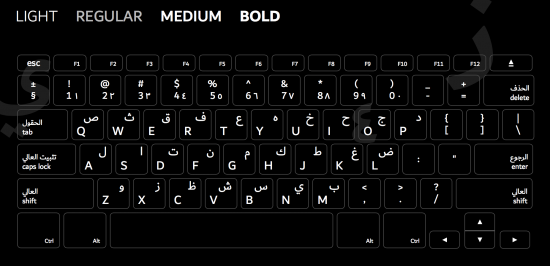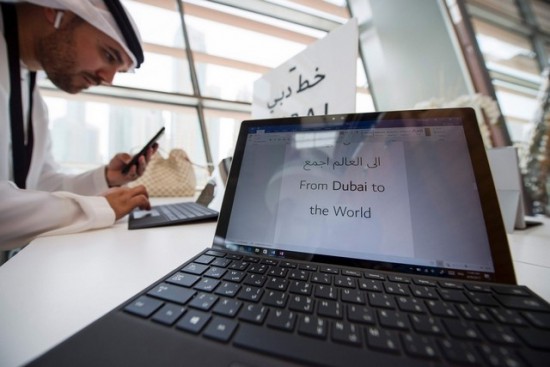
Dubai Font, tipografía de Dubai, que se convierte en la primera ciudad que consigue su propia fuente de Microsoft, árabe y latina.
Dubai se convierte en la primera ciudad que consigue su propia fuente de Microsoft, Dubai Font. La capital de Arabia Saudí, en colaboración con Microsoft, se hace con su propia fuente, desarrollada tanto para caracteres latinos como árabes y disponible en 23 idiomas para las versiones de Microsoft Office. Es decir, accesible para alrededor de 100 millones de usuarios en todo el mundo.
Siete de los diez hoteles más altos del mundo están en Dubai, la ciudad del oro -en el zoco del oro hay más de 300 tiendas que comercian con él-, El Burj Khalifa o el edificio más alto del mundo, taxis sólo para mujeres, los gaiteros de la policía, pista de esquí, paradas de autobús con aire acondicionado y WiFi gratis… y ahora también una tipografía que la utilizarán en su correspondencia todos los organismos oficiales del país.
Dubai Font, presentación
«He supervisado personalmente todas las etapas del desarrollo de este tipo de letra, desde los primeros bocetos de diseño a la fase de ejecución» Príncipe heredero Sheikh Hamdan bin Mohammed bin Rashid Al Maktoum.
Historia de Dubai Font
Un proyecto encargado por el Jeque Hamdan en asociación con Microsoft y desarrollado en Monotype, en concreto por la diseñadora libanesa Nadine Chahine y su equipo. El objetivo era diseñar una fuente de alta calidad, una familia completa con 4 pesos (light, regular, media y gruesa) y que tuviera armonía entre los caracteres en latín y árabe.
Es la primera fuente que se ha diseñado tanto para el alfabeto latino como en árabe al mismo tiempo. Su inspiración está fuertemente arraigada en el patrimonio local -una mezcla de Muhaqqaq y Naskh– para el árabe y el diseño holandés (pragmatismo y funcionalismo neerlandés) para el alfabeto latino. Un estilo moderno e innovador, que sigue la estética tradicional, pero el tratamiento es muy contemporáneo y limpio.
Dubai font light
Dubai font regular
Dubai font medium
Dubai font bold
Dubai es una fuente que se inspira en la ciudad, un tipo moderno pero que desea unir la tradición, la herencia (inspirada en la caligrafía árabe tradicional) y la innovación. En la descripción que se hace de esta fuente en su página no faltan calificativos tan manidos como: joven, dinámico o lleno de pasión y energía. Otros valores que se desean transmitir a través de la fuente son armonía, respeto, tolerancia, expresión personal… aunque quizás para llegar a esto se necesita algo más que una fuente tipográfica. La etiqueta o hashtag que acompaña a la fuente es #expressyou.
Lo importante es, sin duda, la calidad del diseño de la fuente (no podría ser de otra forma), bien optimizada para la lectura en pantalla, con alta legibilidad y libre para su uso en todo tipo de diseños o aplicaciones, privadas y comerciales.
From Dubai to the World
Nadine Chahine @arabictype
Es una joven tipógrafa libanesa (1978, Beirut), que trabaja como experta en tipografía árabe para las empresas Linotype y Monotype Imaging. Estudió diseño gráfico en la Universidad Americana de Beirut y luego realizó un master de diseño tipográfico en la Universidad de Reading (en Reino Unido) así como un doctorado en la Universidad de Leiden (en Países Bajos).
Nadine Chahine creadora de Dubai font
Uno de sus principales objetivos es el de realizar tipografías en árabe de calidad, y también trabajar en la adaptación al árabe de ciertos tipos de letra occidentales como el tipo Univers de Adrian Frutiger o el Zapfino de Hermann Zapf. Otra de sus preocupaciones es que los caracteres en árabe y en alfabeto latino de sus creaciones tengan el mismo aspecto visual.